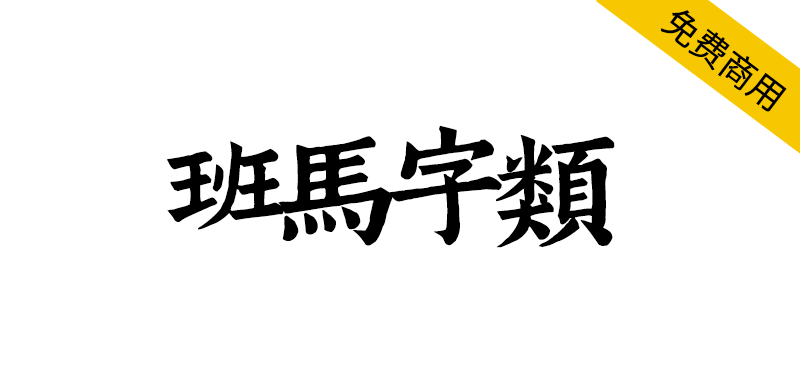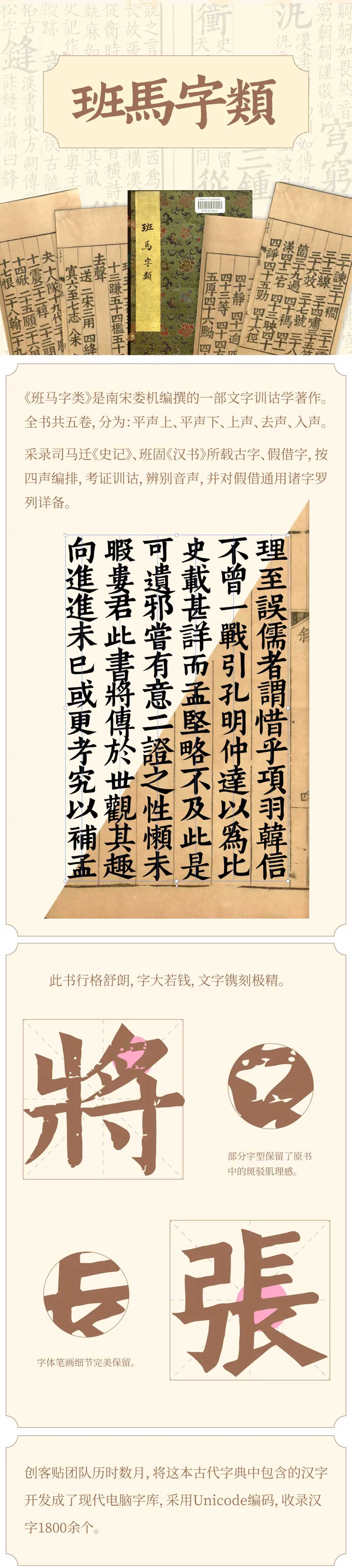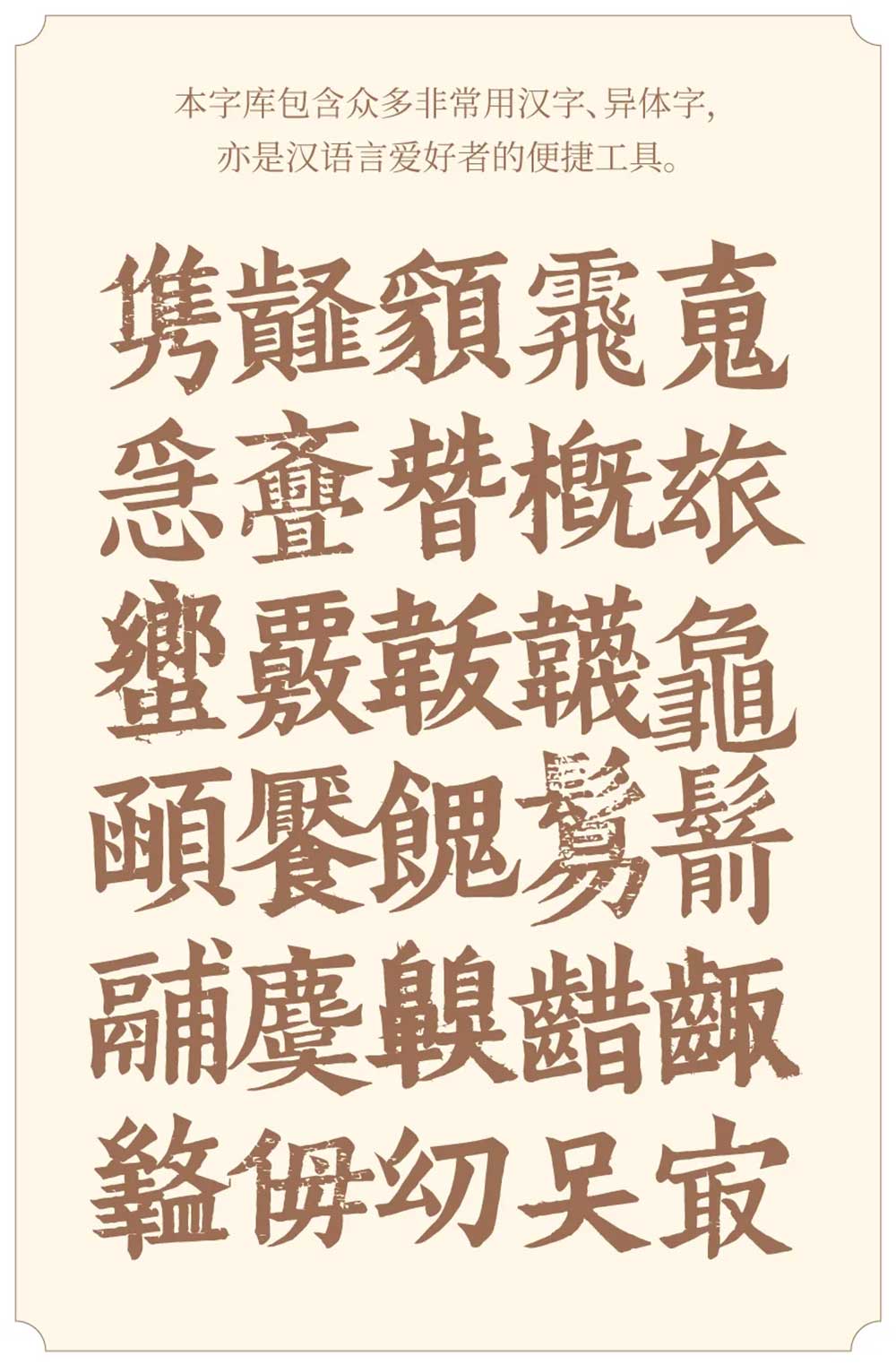
《斑马字类》是南宋娄机编撰的一部文字训诂著作。全书共五卷,分为:平声上、平声下、上声、去声、入声。采录司马迁《史记》、班固《汉书》所载古字、假借字,按四声编排,考证训诂,辨别音声,并对假借通用诸子罗列详备。此书行格舒朗,字大若钱,文字镌刻极精。部分字型保留了原书中的斑驳肌理感。字体笔画细节完美保留。
创客贴团队历时数月,将这本古代字典中包含的汉字开发成了现代电脑字库,采用Unicode编码,收录汉字1800余个。本子库包含众多非常用汉字、异体字,亦是汉语言爱好者的便捷工具。